اهمیت انتخاب فونت در طراحی سایت حرفه ای
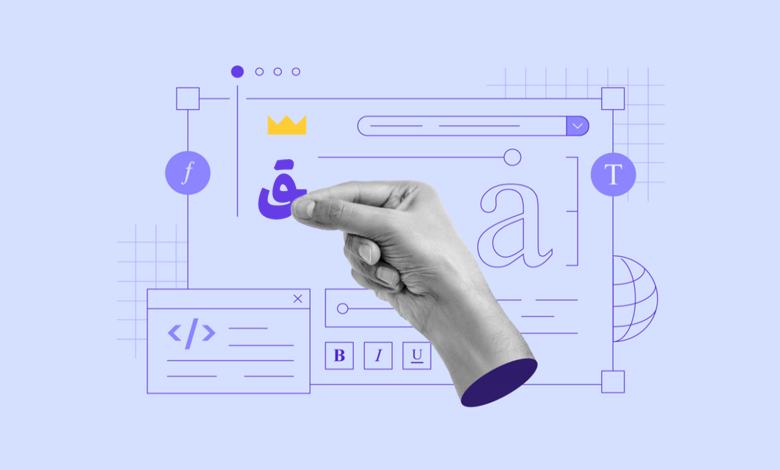
آیا میدانید ۷۵٪ از کاربران، طراحی سایت شما را معیاری برای قضاوت درباره اعتبار برندتان میدانند؟ اهمیت انتخاب فونت در طراحی سایت یکی از عوامل کلیدی است که میتواند منجر به جذب یک مشتری وفادار یا از دست دادن وی شود.
فونتها شاید چیز سادهای بهنظر برسند؛ ما در واقعیت نقش بهسزایی در انتقال پیام برند و تجربه کاربری دارند. از تاثیرگذاری بر خوانایی متنها گرفته تا ایجاد هویت بصری هماهنگ با برندتان؛ انتخاب فونت مناسب میتواند سایت شما را از رقبا متمایز کند و حس حرفهای بودن و اعتماد را به مخاطبان القا کند.
در این مقاله، به شما نشان خواهم داد که چگونه با انتخاب بهترین فونت، تجربه کاربری و هویت برند خود را متمایز کنید. با ما همراه باشید تا گام به گام، راهکارهای انتخاب فونت مناسب و تاثیر آن بر طراحی سایت حرفهای را با هم بررسی کنیم.
اهمیت انتخاب فونت در طراحی سایت حرفه ای
فونت در طراحی سایت، فراتر از یک عنصر زیباییشناسی ساده است. شاید جالب باشد که بدانید انتخاب فونت مناسب میتواند تاثیر عمیقی روی تجربه کاربری (UX)، خوانایی محتوا و حتی سئو (SEO) داشته باشد. در ادامه، به اهمیت انتخاب فونت در طراحی سایت میپردازیم.
تاثیر فونت بر تجربه کاربری (UX)
تجربه کاربری یا User Exprience به معنی نحوه تعامل کاربران با سایت شما است. به عبارت سادهتر نشان میدهد که کاربران با توجه به طراحی سایت شما، چه رفتاری در بخشهای مختلف دارند و این رفتار تا چه اندازه مشخص است.
اگر کاربران نتوانند به راحتی محتوای سایت شما را بخوانند یا ساختار طراحی سایتتان برای آنها پیچیده بهنظر برسد، احتمالا از آن خارج خواهند شد. انتخاب فونت مناسب باعث میشود که محتوای سایت شما به راحتی قابل خواندن باشد، از این رو کاربر احساس راحتی بیشتری در هنگام مرور صفحات مختلف سایت خواهد داشت.
یک فونت مناسب میتواند حس راحتی و اعتماد را در کاربران ایجاد کند و آنها را ترغیب به ماندن در سایت و کاوش بیشتر کند.
تاثیر فونت در خوانایی محتوای سایت
اصلیترین نکته در طراحی وبسایت، توجه به خوانایی محتوا است. اگر فونت سایت خیلی ریز، خیلی درشت، یا خیلی پیچیده باشد، خواندن متنها برای کاربران سخت خواهد شد. فونتهای خوانا و بهدنبال آن با اندازه مناسب، تجربه مطالعه را آسانتر میکنند و اطلاعات را به شیوهای موثرتر منتقل میکنند.
بهخصوص در سایتهای فروشگاهی، اگر مشتری نتواند به راحتی توضیحات محصول یا جزئیات مهم را بخواند، احتمالا به سرعت سایت شما را ترک خواهد کرد.
تاثیر فونت در سئو سایت
این تاثیر غیرمستقیم است. فونتهای پیچیده یا فونتهایی که به هر دلیلی موجب کاهش سرعت بارگذاری صفحات میشوند، تاخیر در بارگذاری سایت را بهدنبال دارند که یکی از عمدهترین دلایل تجربه کاربری نامناسب همین مسئله است. به همین دلیل است که توصیه میشود فونتها را همیشه بهصورت swap لود کنید.
به علاوه، سایتهایی که طراحی ساده و در عینحال لود سریع دارند، بیشتر مورد توجه موتورهای جستجو قرار میگیرند. در نتیجه رتبه بهتری در نتایج جستجو خواهند گرفت.
هماهنگی فونت با هویت برند
فونتها میتوانند هویت برند شما را به وضوح نشان دهند. برندهای معروف و بزرگ معمولا فونتهای خاص و منحصر به فردی دارند که آنها را از دیگران متمایز میکند. بهعنوان مثال شرکتهایی چون علیبابا و ایرانسل را درنظر بگیرید که فونت اختصاصی خود را دارند.
انتخاب فونت مناسب و هماهنگ با شخصیت برند سایت را از نظر بصری جذابتر میکند. به عنوان مثال، فونتهای مدرن و مینیمال برای برندهای فناوری یا استارتاپها مناسب است، در حالی که فونتهای کلاسیکتر و رسمیتر برای برندهای حقوقی یا مشاورهای یا فونتهای فانتزی نرم و دوستانه برای سایتهای کودکانه کارایی بیشتری دارند.
تاثیر فونت روی دسترسی پذیری (Accessibility)
فونتهای نامناسب میتوانند بر دسترسیپذیری سایت تاثیر منفی بگذارند. کاربران با مشکلات بینایی مانند دیسکالریا (نابینایی رنگی) یا ضعف بینایی ممکن است نتوانند متنها را به راحتی مطالعه کنند. استفاده از فونتهای خوانا و با فاصلههای مناسب باعث میشود که همه کاربران، از جمله کسانی که نیازهای خاص دارند، بتوانند از سایت شما استفاده کنند. این مورد بهخصوص برای سایتهایی که نیاز به دسترسیپذیری بالا دارند، حیاتی است.
ویژگی های فونت حرفه ای برای سایت
در انتخاب فونت مناسب برای طراحی سایت حرفهای، توجه به جزئیاتی مانند خوانایی، هماهنگی با هویت برند، سازگاری با زبان فارسی و عملکرد در دستگاههای مختلف، ضروری است.
- خوانایی (Legibility): کاربران باید بتوانند بهراحتی محتوای سایت شما را مطالعه کنند. فونتهای ساده، متناسب با اندازه مناسب (بین ۱۴ تا ۱۶ پیکسل برای متنهای بدنه) و با فاصله خطوط کافی (حداقل ۱.۵ برابر اندازه فونت) تجربه کاربری بهتری فراهم میکنند.
نکته: استفاده از فونتهای بسیار فانتزی یا بیش از حد ریز، تجربه مطالعه کاربران را دشوار میکند.
- هماهنگی با هویت برند (Brand Identity): فونت، یکی از ابزارهای اصلی در ایجاد هویت بصری برند است. اگر سایت شما برندی خلاقانه یا مدرن است، میتوانید از فونتهای مینیمال و مدرن مانند ایران سنس یا شبنم استفاده کنید. برای برندهای سنتی یا رسمی، فونتهایی مثل وزیرمتن یا ایران یکان که حس اطمینان و قدرت را منتقل میکنند، انتخاب بهتری هستند. بهطور کلی فونت سایت باید پیام و ارزشهای برند شما را منعکس کند تا کاربران حس یکپارچگی را از هویت برندتان دریافت کنند.
- سازگاری فونت با زبان: یکی از چالشهای مهم طراحی سایت فارسی، انتخاب فونتی است که بهخوبی با زبان فارسی سازگار باشد. بسیاری از فونتهای غیربومی، برای حروف فارسی بهینه نشدهاند و ممکن است مشکلاتی در چینش، فاصلهها، اعرابگذاری و ظاهر کلی داشته باشند. استفاده از فونتهای فارسی استاندارد مانند ایران یکان، وزیر و ساحل میتواند محتوای شما را حرفهایتر نشان دهد.